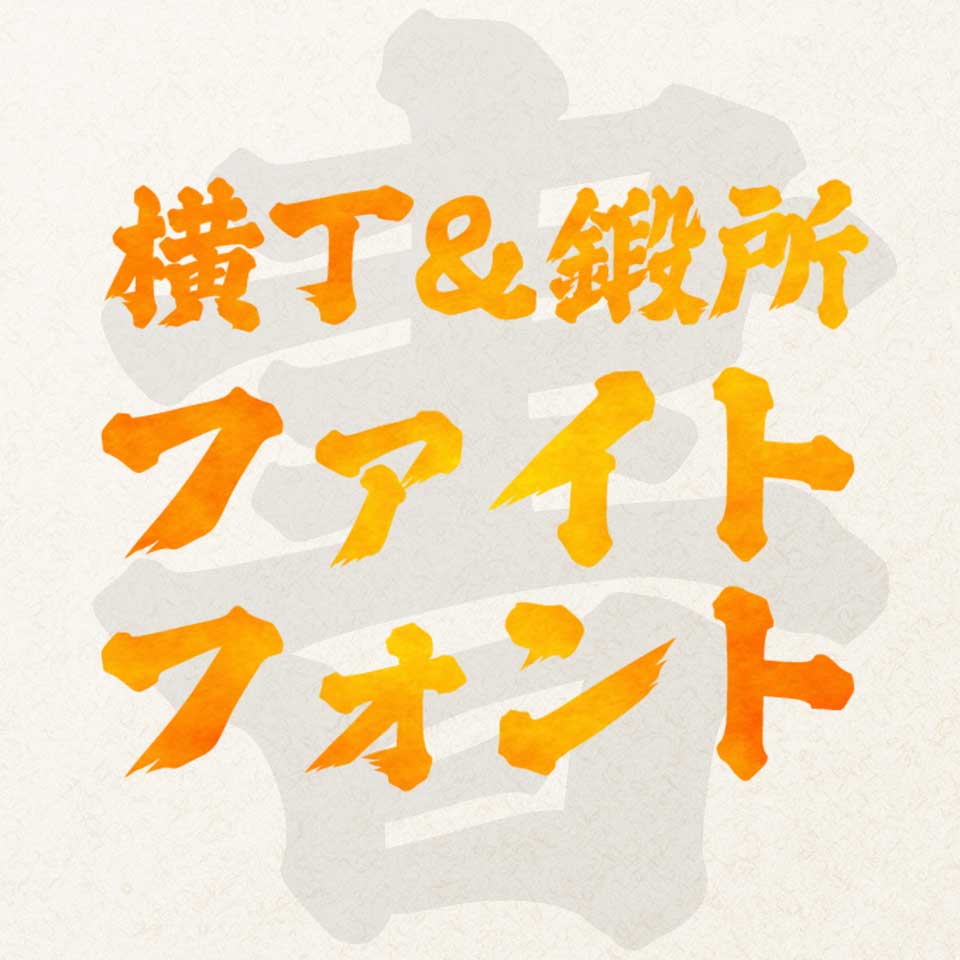
フォント村の筆横丁やマール社書籍の書体を高機能化&初デジタル化
古今東西、珍しい情報をお届けする「六葉情報 (むつばじょうほう) 」。かつて「フォント村の筆横丁」から提供されていた「あまから」「ファイト」、そしてマール社の書籍に掲載・王超鷹氏の手による伝統筆文字を、それぞれ高機能化・初デジタル化し新版フォントとしてリリースしています。
高機能化された新しい『あまから』『ファイト』
かつて「フォント村の筆横丁」から提供されていた「あまから」と「ファイト」のデータを1年かけて修正し互換性・機能性を高めた新版フォントです。閉鎖した元の製造者から改造・販売許可を得た純正品ですので、安心してご使用ください。
仮名の濁点、英数字、ローマ字、記号などの文字デザインの修正、異体字や令和の追加、プローポーショナル間隔、等幅間隔、それぞれの横書き、縦書きの調整を行いOpenTypeフォントとして、かつての名作フォントを蘇らせました。
常用の〝横丁〟と加工用の〝鍛所 (たんどころ)〟を同梱
「あまから」「ファイト」どちらも、一般的なアウトラインで作られた常用の〝横丁〟フォントとは別に、文字を構成している1つ1つのパーツを折り重ね、必要に応じて分解が可能な〝鍛所〟フォントも同梱しています。
鍛所フォントも、入力しただけでは通常用の横丁フォントと変わりがありません。
Illustrator等のアプリケーションで、中とアウトラインの色を変えると、複数のパーツで構成されていることが分かります。
パスに変換して、分割して、文字パーツごとに色付することができます。
文字パーツごとに変形することもできます。自由な発想で文字を編集・加工することができます。
王超鷹先生のデジタル書体編『馬王・兎臣シリーズ』
「馬王シリーズ」は、伝統工芸士・文化研究者でもあるデザイナー 王超鷹先生による書体。マール社刊「草書体字典」に掲載の文字をベースに、原作者より許諾を得てつくられました。
「兎臣シリーズ」は、馬王シリーズに非破壊的なボールド加工を当てて作られたシリーズ。画が太い、すっきりした筆文字となります。
おすすめの使い方
同人誌のタイトルや見出し、ロゴなど
使用フォント:ファイトフォント
チラシ・フライヤー・広告など
使用フォント:あまからフォント、馬王顔書
挨拶状・手紙・メモ・メッセージなど
使用フォント:馬王行書、馬王楷書
書体一覧
1. 横丁&鍛所 あまからフォント
横丁・鍛所それぞれ、文字ピッチの異なる4種類のフォントを同梱しています。
▼ あまから…半角欧文はプロポーショナルピッチ、その他は固定ピッチ
▼ あまからT…半角欧文・非漢字・漢字がすべて固定ピッチ
▼ あまからK…半角欧文・全角仮名はプロポーショナルピッチ、その他は固定ピッチ
▼ あまからP…漢字以外のすべてがプロポーショナルピッチ
あまからフォント
あまからフォントは、丸みを帯びた極太の毛筆書体で、暖かくて優しい親しみやすい印象を持っています。タイトルや見出し、ロゴなどにおすすめです。
2. 横丁&鍛所 ファイトフォント
横丁・鍛所それぞれ、文字ピッチの異なる4種類のフォントを同梱しています。
▼ ファイト…半角欧文はプロポーショナルピッチ、その他は固定ピッチ
▼ ファイトT…半角欧文・非漢字・漢字がすべて固定ピッチ
▼ ファイトK…半角欧文・全角仮名はプロポーショナルピッチ、その他は固定ピッチ
▼ ファイトP…漢字以外のすべてがプロポーショナルピッチ
ファイトフォント
ファイトフォントは、勢いのあるはらいが特徴的な極太の毛筆書体で、荒々しく力強い印象を持っています。タイトルや見出し、ロゴなどにおすすめです。
3. 馬王草書+兎臣草書セット
馬王草書
踊る筆の豪華な草書体。昔懐かしい印象を与えるフォントです。
兎臣草書
馬王草書に非破壊的なボールド加工を当てた、すっきりした特太草書体です。
馬王草書+兎臣草書セット
馬王草書 兎臣草書
馬王草書は、マール社刊「草書体字典」に掲載の書体をベースに、原作者より許諾を得て製造されました。兎臣草書は、フォント開発工程で非破壊的なボールド加工を馬王草書に当てた結果、画の太い、すっきりした特太草書体です。
4. 馬王行書+兎臣行書セット
馬王行書
踊る筆の豪華な行書体。清流の印象を持つフォントです。
兎臣行書
馬王行書に非破壊的なボールド加工を当てた、すっきりした特太行書体です。
馬王行書+兎臣行書セット
馬王行書 兎臣行書
馬王行書は、マール社刊「新行書体」に掲載の書体をベースに、原作者より許諾を得て製造されました。兎臣行書は、フォント開発工程で非破壊的なボールド加工を馬王行書に当てた結果、画の太い、すっきりした特太行書体です。
5. 馬王楷書+兎臣楷書セット
馬王楷書
たっぷりとした筆使いの豪華な楷書体。クラシック且つ新たな味を持つフォントです。
兎臣楷書
馬王楷書に非破壊的なボールド加工を当てた、すっきりした特太楷書体です。
馬王行書+兎臣行書セット